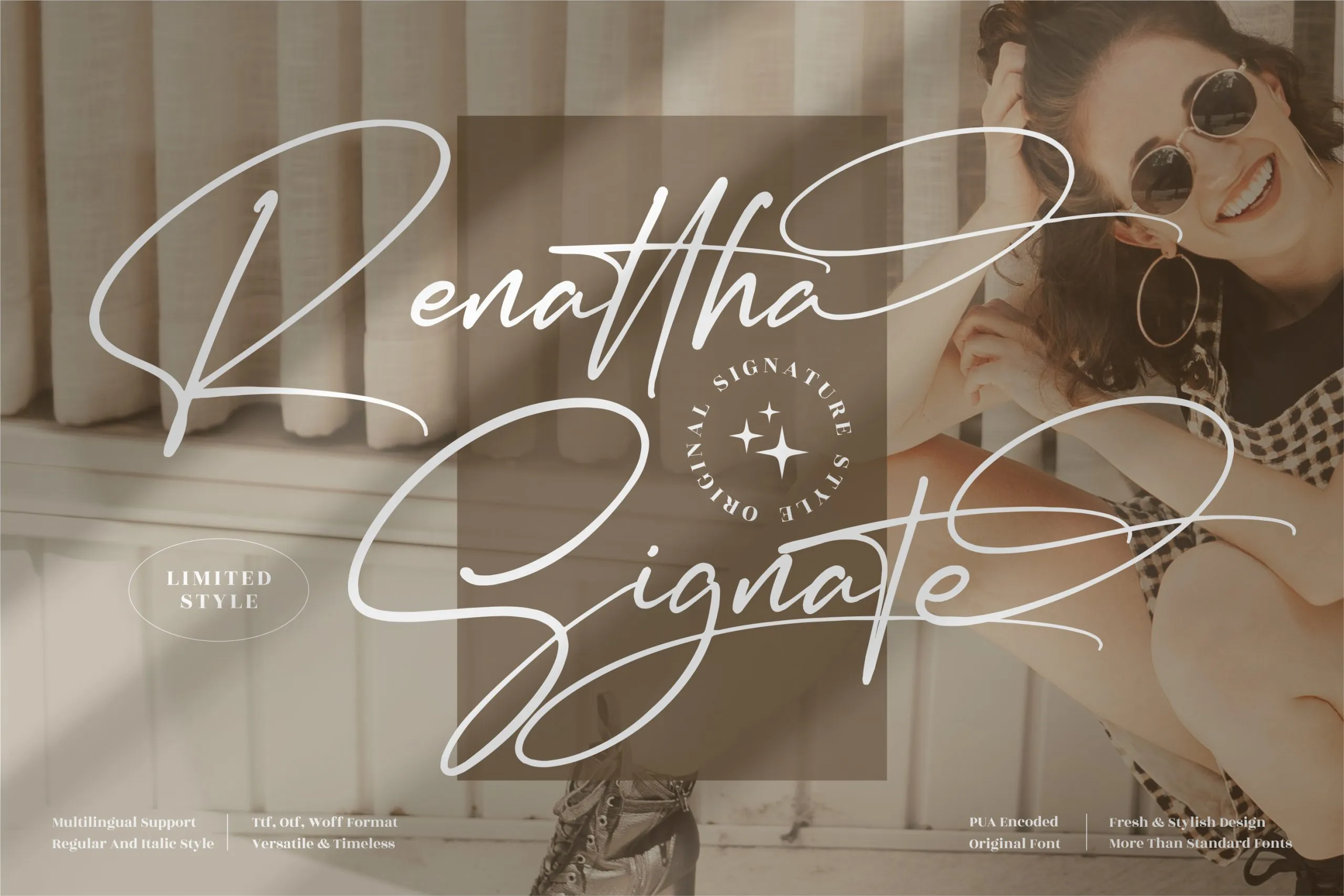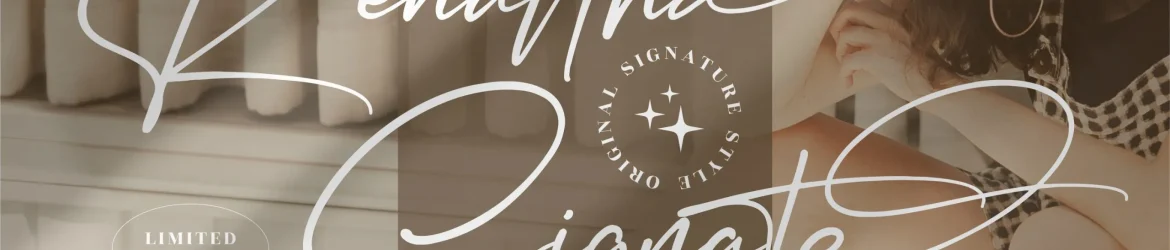
A Renattha Signate Font é uma escolha perfeita para projetos que exigem um toque elegante e sofisticado. Desenvolvida pelo estúdio Perspectype Studio, essa fonte de assinatura premium se destaca em diversos ambientes, desde cartões de nome até capas de livros, passando por banners, adesivos e etiquetas personalizadas. Suave e elegante, Renattha Signate oferece uma paleta de opções de escrita que podem ser facilmente adaptadas para sua necessidade específica. A fonte é perfeita para designers criativos buscam um toque único em seus trabalhos, seja para criar marcas de empresas sofisticadas ou para personalizar produtos exclusivos e colecionáveis. Seja qual for seu projeto, a Renattha Signate Font é uma opção ideal para levar sua ideia a um nível ainda mais alto.